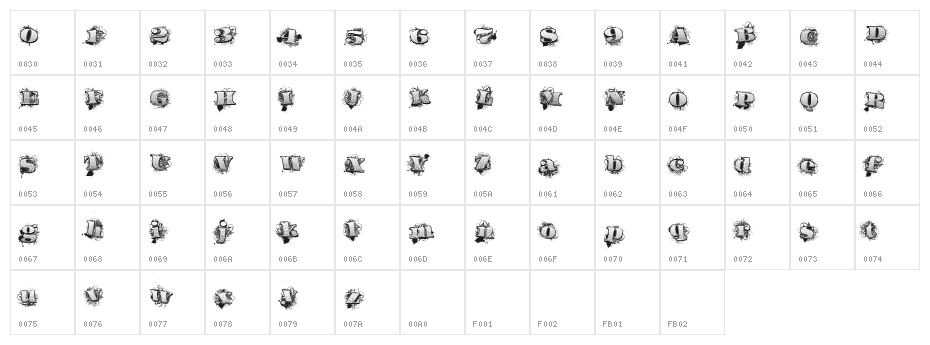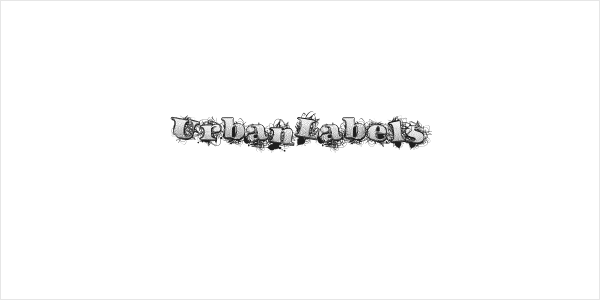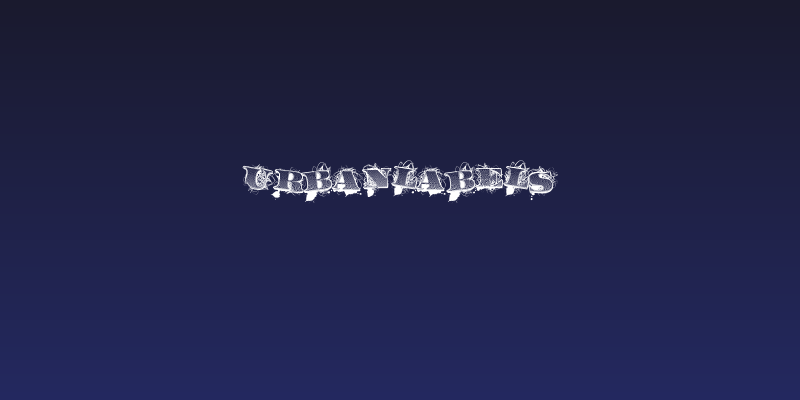
UrbanLabels Font
✎ Distorted Eroded
| Categorie | Distorted Eroded |
| Stile generale | Urban, Artistic, Edgy |
| Caso d'uso | Logos, Posters, Branding |
| Progetti proposti | Ideal for streetwear branding, music album covers, urban-themed posters, and graffiti art projects. |